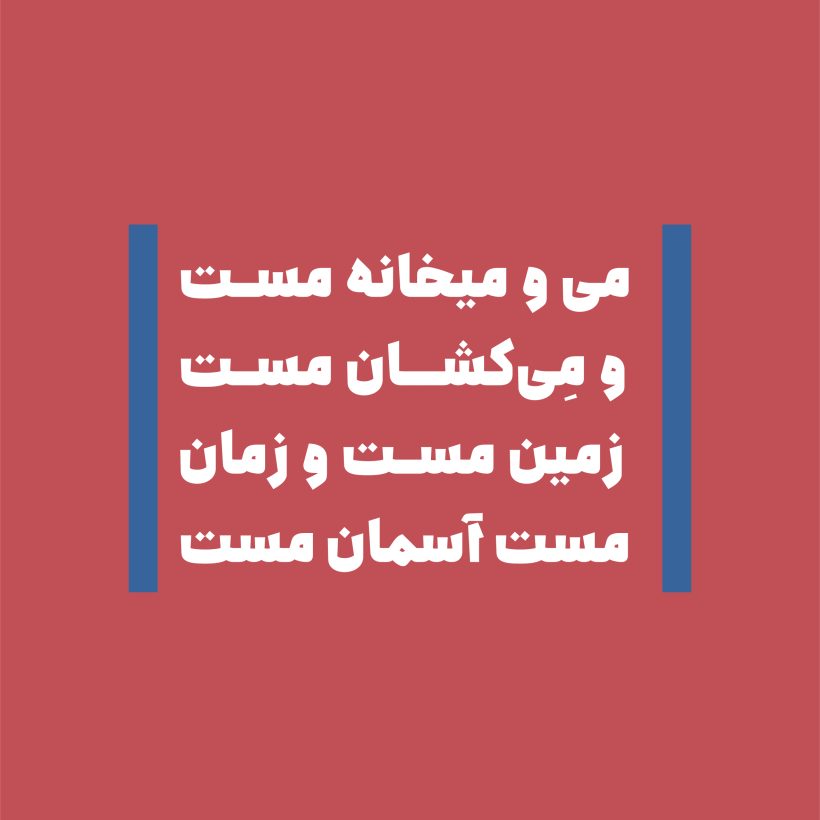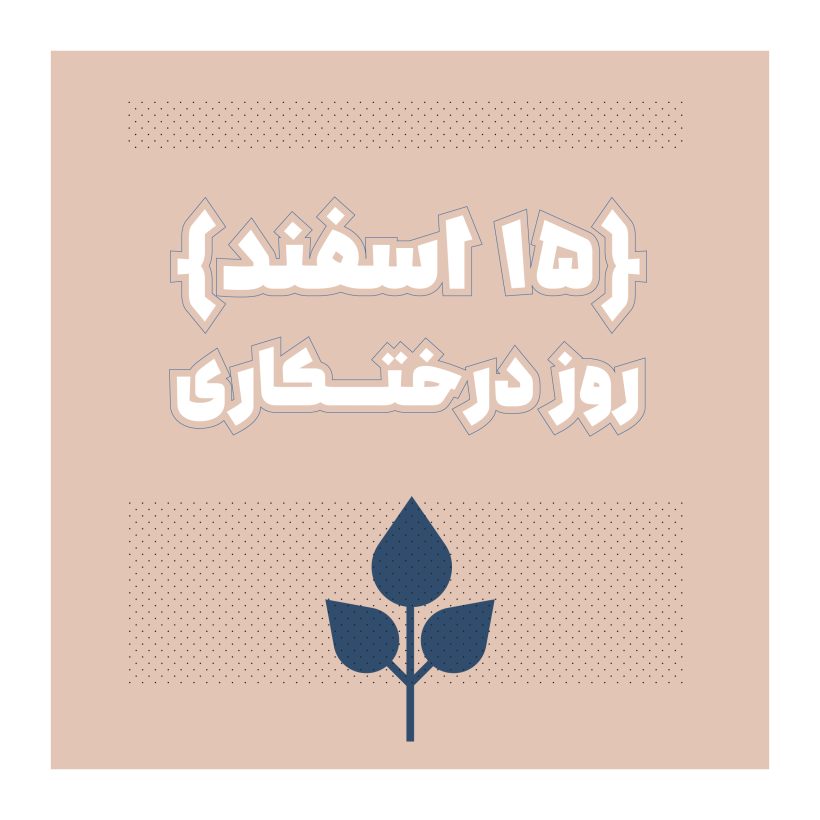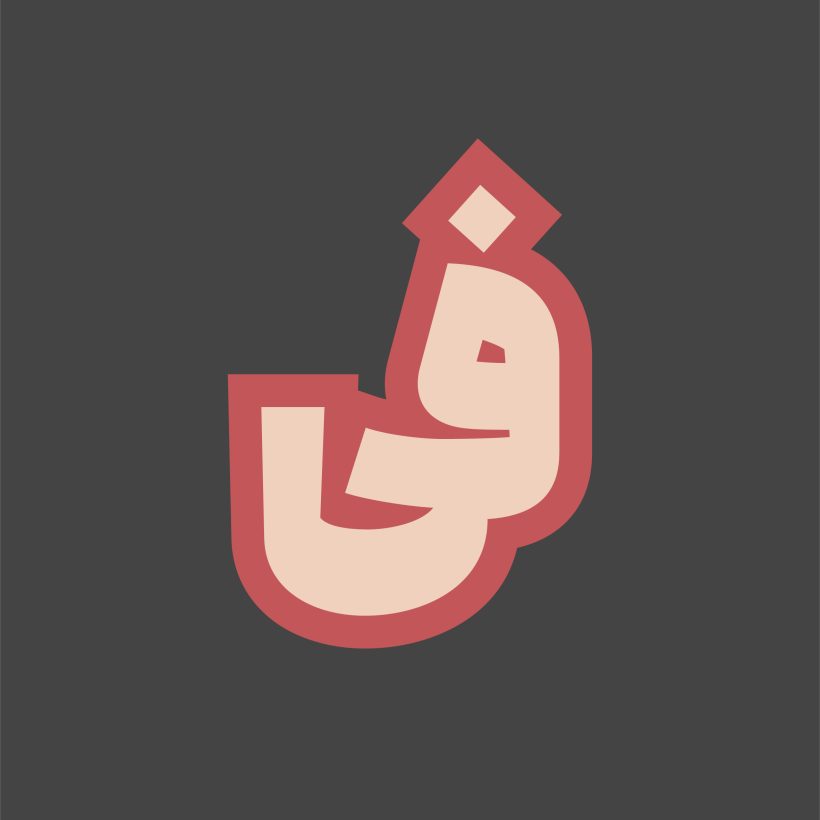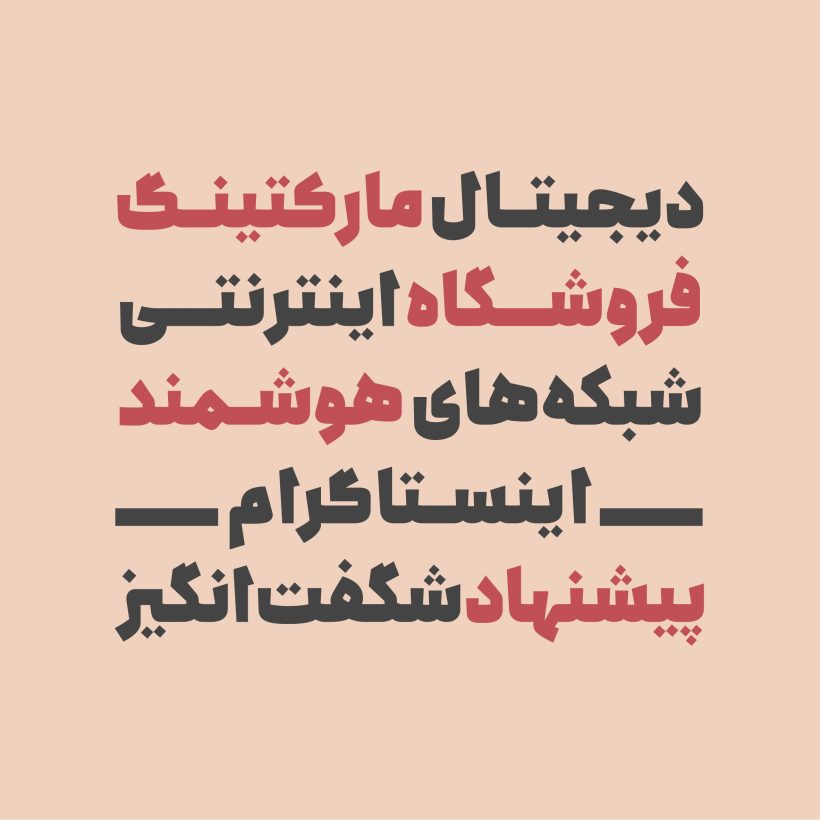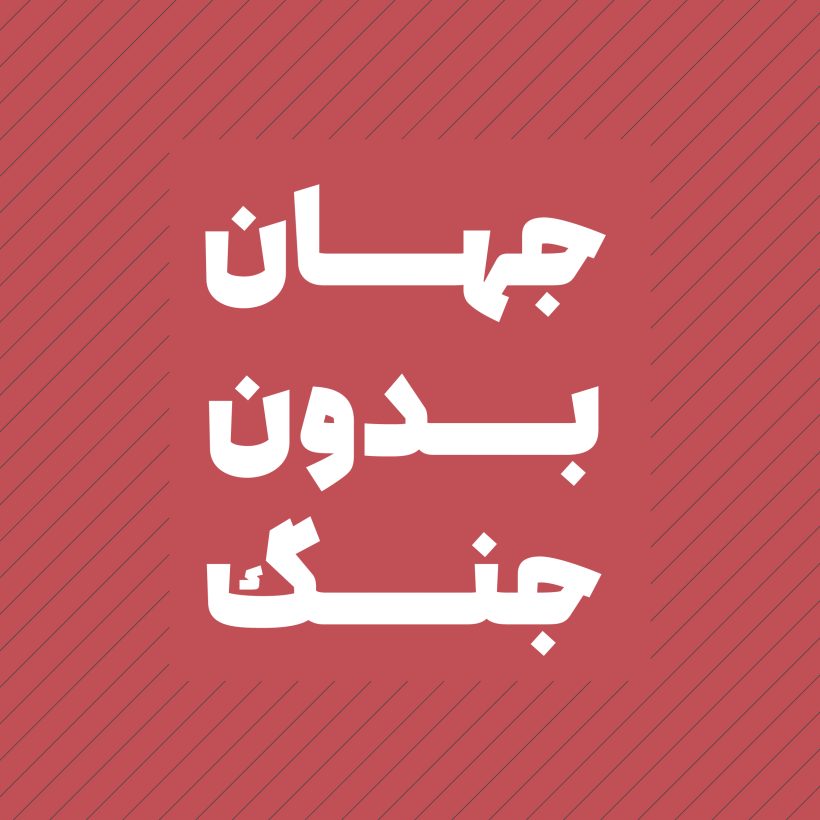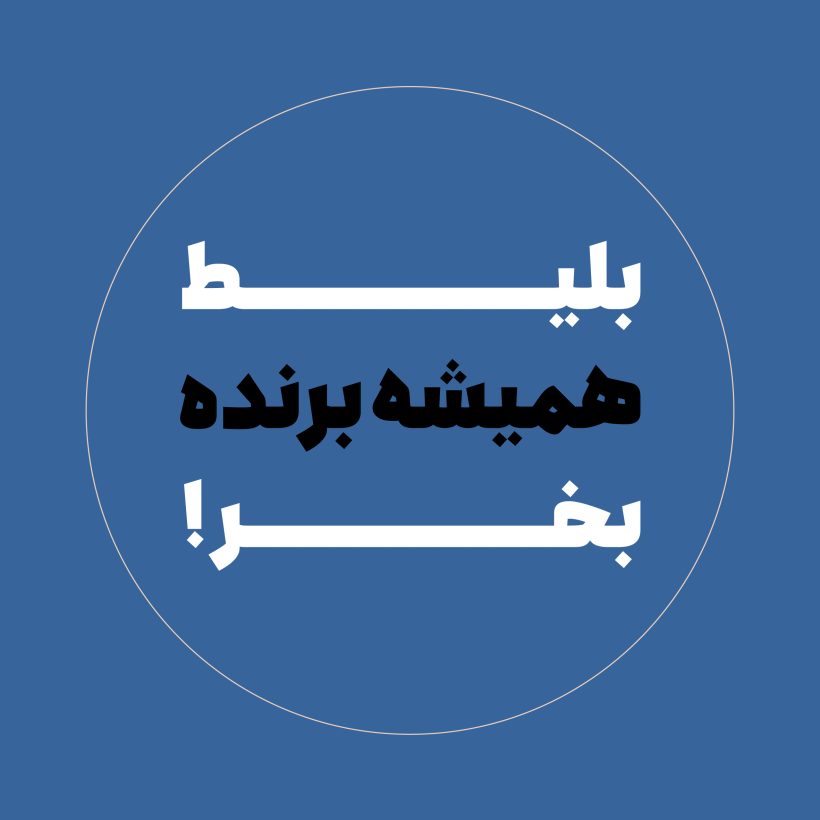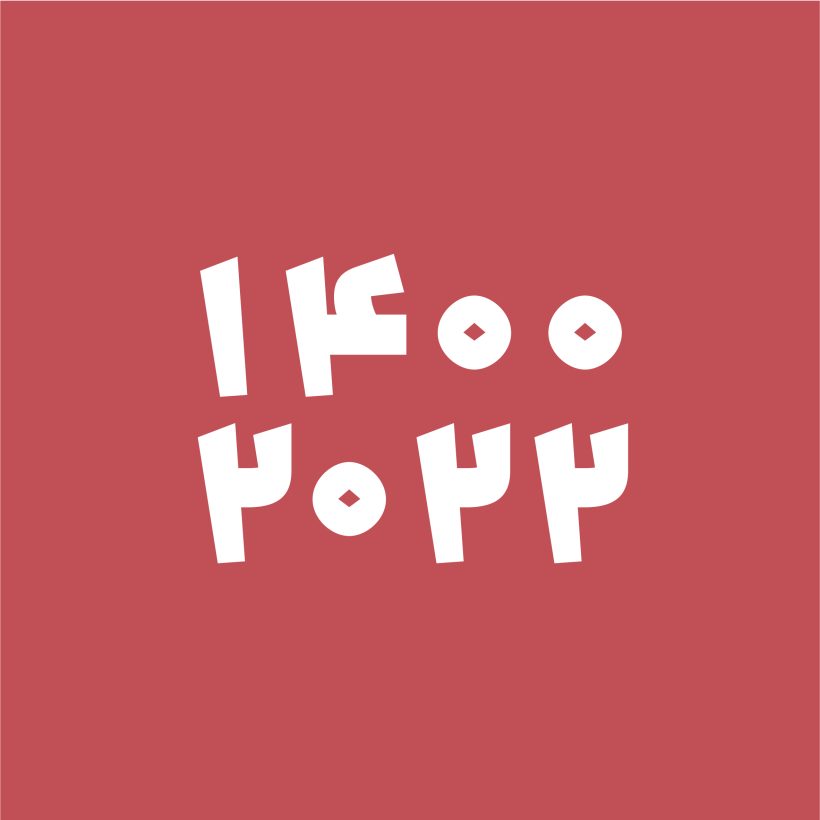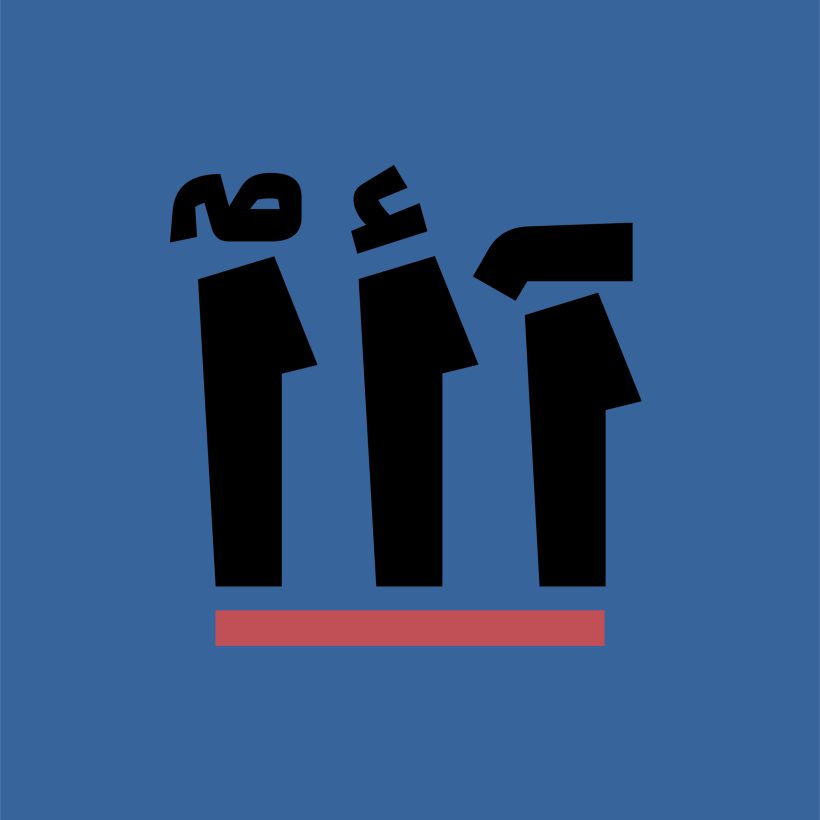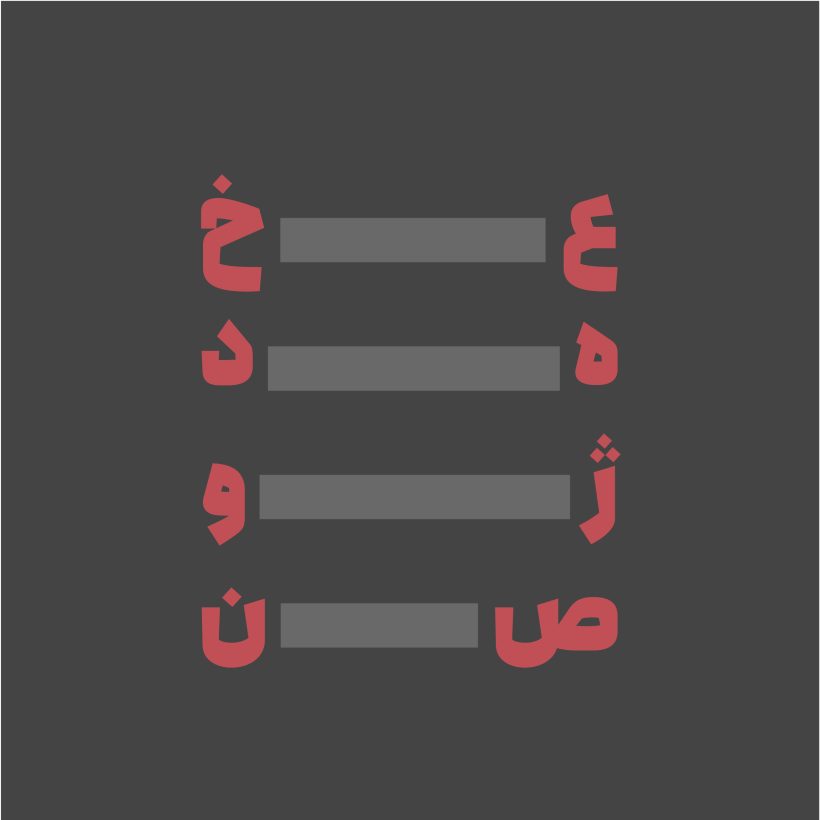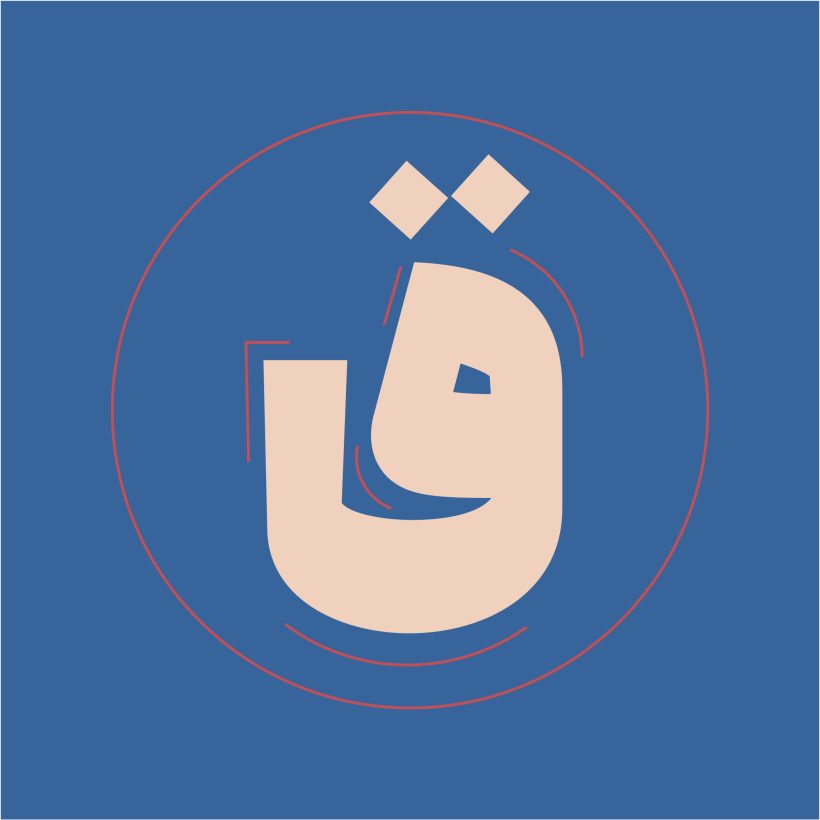
خانواده فونت جلایر
خطوط ناشناخته سکه های ضرب شده کهن با لحن های متفاوت و جالب توجهی که دارد، می تواند الهام بخش ایده هایی نو برای طراحان فونت معاصر باشد و فونت جلایر با الهام از خط ناشناخته سکه نقره احمد جلایری محفوظ در کتابخانه ملک طراحی شده است.
جلایر فونتی نمایشی است و در چهار وزن طراحی شده است و برای تیترها، عناوین، عبارت های کوتاه، تیزرها و امور تبلیغاتی مناسب به نظر می رسد. استروک های فونت جلایر در گردش های قلم دارای زوایای مشخصی است و دور حروف در جلایر کمتر شده و از حرکات مورب بیشتری برخوردار است. دوایر نون و اشکال مشابه آن تا حد ممکن جمع و جور طراحی شده است. در فونت جلایر، کشیده های عمودی کوتاه قامت اند و تا حد ممکن تلاش شده اغلب حرکات حروف نزدیک به خط زمینه یا کرسی وسط طراحی گردد.
قواعد کرنینگ و اعراب گذاری ها در فونت جلایر اعمال شده است. جلایر دارای لیگیچر و کارکترهای جایگزین است تا برحسب نیاز و برای زیبایی بیشتر به کار گرفته شود.
فونت جلایر با راهنمایی استاد صداقت جباری و توسط معصومه مصلح در سال 1400-1401 طراحی شده است.